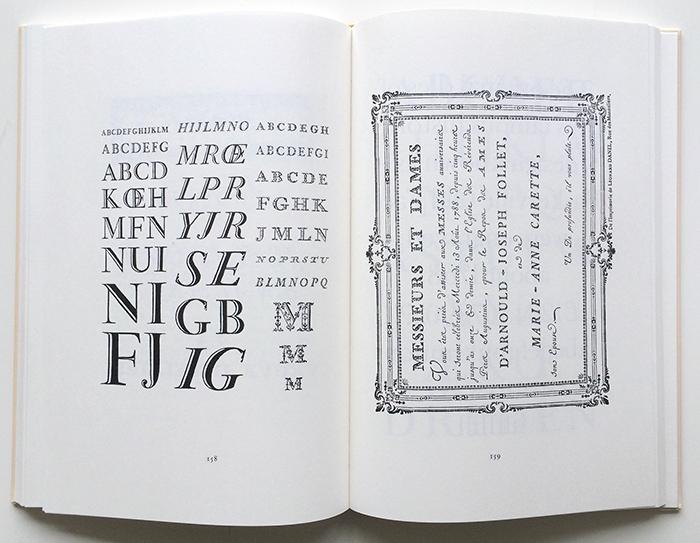
Jan Tschicholds Meisterbuch der Schrift erschien Mitte des 20. Jahrhunderts. Zu dieser Zeit waren fast alle Schriftanwendungen, die nicht mit Druckschriften gesetzt wurden – also zum Beispiel Logos und Schilder aller Art – in Handarbeit als Lettering bzw. Kalligrafie gefertigt. Tschichold war mit der Qualität dieser Arbeit höchst unzufrieden. »Fast alle Schrift die uns begegnet, ist schlecht, ungenügend oder wild. […] Man muß von einem erbärmlichen Tiefstand reden«. Die Ursache sah er in unzureichendem Wissen über Schriftgeschichte bzw. -entwurf und einem »Mangel an guten Vorlagen«. Mit dem Meisterbuch der Schrift wollte Tschichold hier einen Gegenpol setzen. Das Werk richtete sich dabei explizit an Schriftmaler, Grafiker, Bildhauer, Graveure, Lithografen, Verlagshersteller, Buchdrucker, Architekten und Kunstschulen.
Auf den ersten, knapp 50 Seiten gibt Tschichold Einblicke in Schriftgeschichte, Schriftklassifikation und Empfehlungen zum Umgang mit Schrift, etwa zur Zurichtung von Buchstaben und Zeilen oder der Schriftwahl. In typisch tschichold’scher Manier werden die Empfehlung nicht selten wie Gesetze definiert, die keinen Widerspruch dulden.
Darüber hinaus setzt sich Tschichold auch mit einzelnen Buchstaben auseinander. Hier findet sich etwa Tschicholds berühmte und umstrittene These, dass das Eszett auch in gebrochenen Schriften eigentlich eine Ligatur aus ſ und s wäre. Auch äußert er sich zum &, dem ſ in der gebrochenen Schrift (dessen Verzicht er als »Barbarei« bezeichnet), zu Umlauten und zur Unterscheidung von I und J. In der Antiqua wünscht er sich hier ein I ohne Bogen, in den gebrochenen Schriften sieht er in der unterschiedlichen Ausgestaltung der beiden Versalien eine Missgeburt.
Den Rest des Buches machen dann die 176 Schriftmuster-Tafeln aus, in denen Tschichold Alphabete und Anwendungen aus 2000 Jahren lateinischer Schriftkultur präsentiert. Von antiken Inschriften über mittelalterliche Schreibmeister-Blätter bis hin zu modernden Druckschriften des 20. Jahrhunderts erstreckt sich dabei die Auswahl.
Inhalt
- Vorwort
- Schrift als künstlerische Aufgabe
- Gute und schlechte Buchstaben
- Die älteren Schriftarten
Die neueren Schriftarten
- Klassizierung und Benennung der Hauptschriftarten
Der Umgang mit Großbuchstaben
- Der Wortabstand in Großbuchstabenzeilen
- Der Zeilenabstand von Großbuchstabenzeilen
Der Umgang mit Kleinbuchstaben
- Der Wortabstand in Kleinbuchstabenzeilen
- Der Zeilenabstand von Kleinbuchstabenzeilen
Die Wahl der richtigen Schrift
Die Anordnung von Schriftgruppen und Schildern
- Schöne Schildproportionen
Einzelheiten
- Über Herkunft und Form des ß
- Das lange ſ der gebrochenen Schriften
- Von &-Zeichen
- Über die Umlaute und den Unterschied zwischen I und J
Tafeln
Bemerkungen zu den Tafeln
Verzeichnis der Schriftarten und Künstler